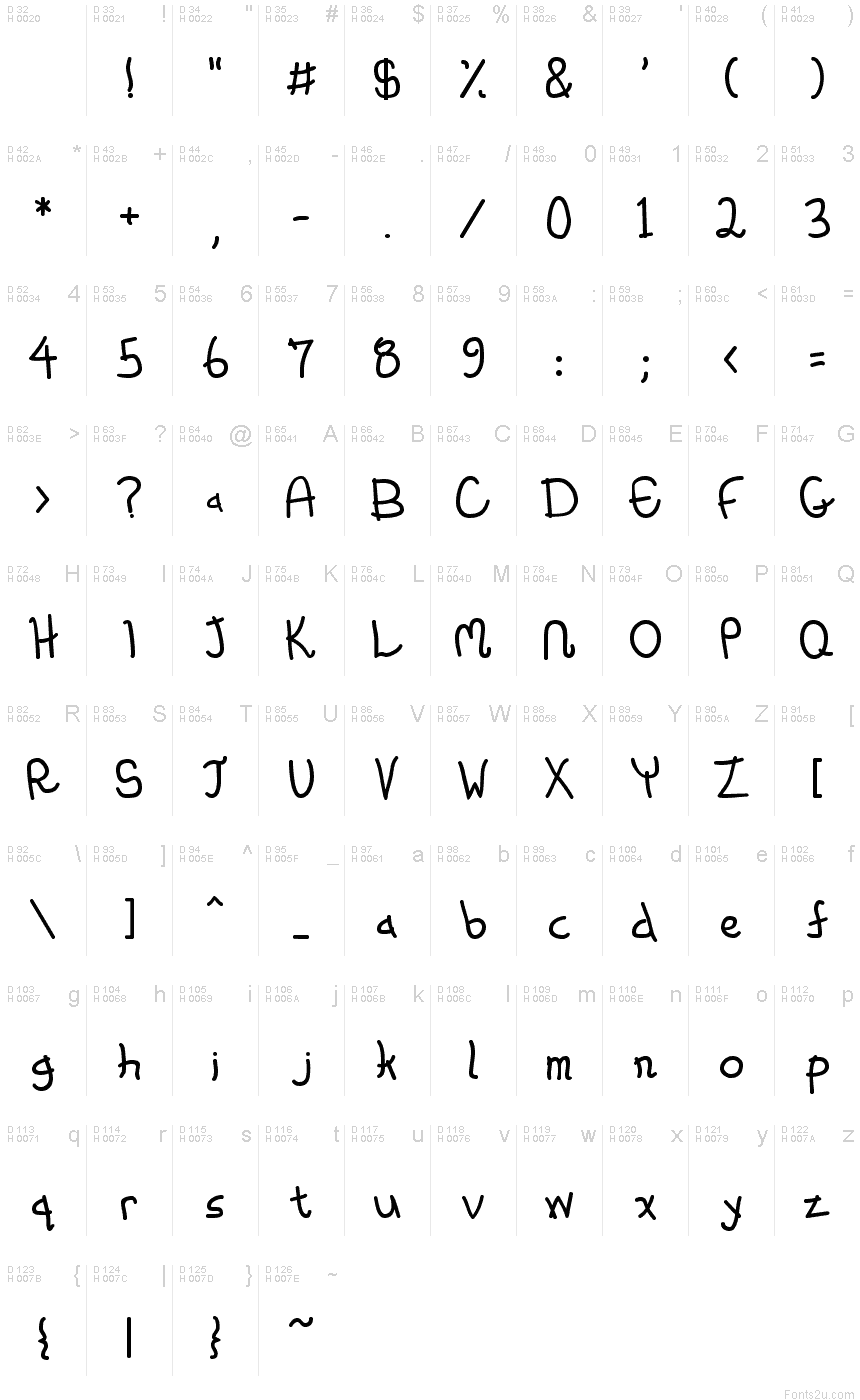
Whimsico، خط مجاني بنمط الكتابة اليدوية من DazzlingDesigns، يتميز بخفة وسرعة حركة الخطوط التي تشبه الكتابة بالقلم العريض، مع إيقاع مرح وغير تقليدي. الحروف تبدو دائرية وغير رسمية، مع ضربات مرتفعة ومنحنيات ناعمة، وعدم انتظام عفوي يمنح الخط طابعاً ودوداً بعيداً عن التكلف.
هذا يجعل هذا الخط المجاني خياراً طبيعياً لأغلفة كتب الأطفال، ورسومات السبورات في المقاهي، وعناوين سجلات القصاصات، ودعوات الحفلات، وتصاميم ترويسات المدونات حيث تهم اللمسة الإنسانية العفوية. كما يعمل بشكل جيد في النصوص القصيرة على العبوات أو منشورات التواصل الاجتماعي، لأن الخطوط الحرة والاختلافات الطفيفة في الارتفاع تمنح الكلمات طابعاً حيوياً ومصنوعاً يدوياً.